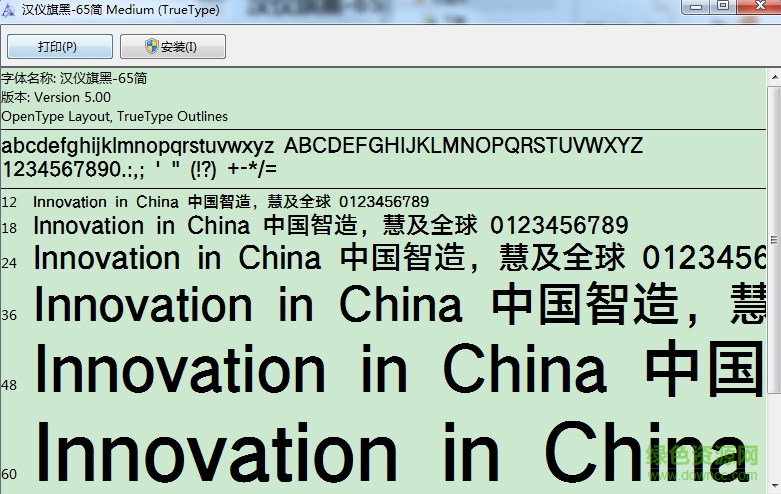
hyqihei fes字體是一款字型優(yōu)美的電腦字體,這款字體擁有樸素大方、結(jié)構(gòu)嚴(yán)謹(jǐn)?shù)奶攸c(diǎn),非常引人注目,使用范圍也是非常廣泛,可以運(yùn)用到了各個(gè)領(lǐng)域中,有需要的朋友歡迎下載使用!
hyqihei fes字體又稱漢儀旗黑65,漢儀旗黑字體中的一款,字體寫出來(lái)的字是十分工整的,整體效果非常出色,非常適用于書(shū)本印刷、廣告設(shè)計(jì)等領(lǐng)域!